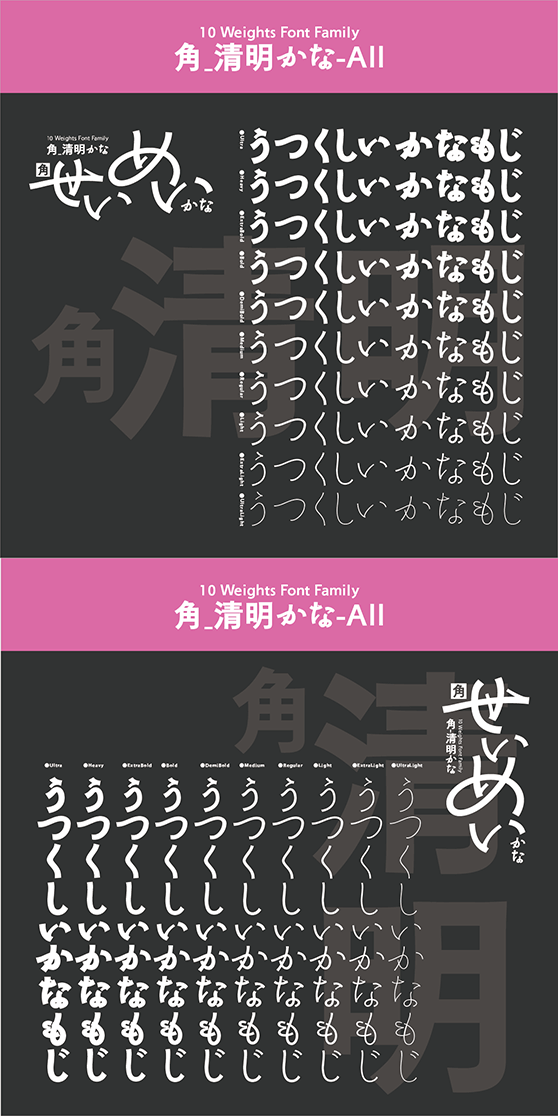
角_清明かな-All (10書体セット)
Kaku_SeimeiKana-UL, Kaku_SeimeiKana-EL, Kaku_SeimeiKana-R, Kaku_SeimeiKana-M, Kaku_SeimeiKana-DB, Kaku_SeimeiKana-EB, Kaku_SeimeiKana-H, Kaku_SeimeiKana-U
優しさと切れ味をあわせ持つかなフォント
この書体は、大好評を得ている「清明かな」のゴシック版として開発されたものです。書体名の「清明(せいめい)」は、季節の指標である「二十四節気」の5番目の節気のこと。春の息吹があふれ「すべてのものが清らかで生き生きしている」という意味です。その名の通り、伸びやかな切れ味の中に優しさ・優美さを包含した不思議な書体です。
タイプデザイナー金井和夫の普段使いの文字をベースとした、明朝・行書・楷書の複雑なフォルムイメージを持っています。また、オールドなイメージを残しつつも、その概念にとらわれず大仮名に設計してあり、近代的な組版にも対応するマルチな性格を備えています。
角_清明かなは、クリエイティブワークに「躍動感と訴求力を表現する」一助にと開発されました。和文フォントは、正方形の中に押し込めることにより、伸びやかさがなくなる傾向があります。この書体は必ずしも正方形にとらわれない自由な発想で作られています。特徴が強く、長文には不向きですが、短い本文組みや、手紙文、ちょっとした見出しに使ってみてください。躍動感に満ちた、訴求力のある紙面になるはずです。縦組み、横組みともプロポーショナル加工を加えました。また、ペアカーニングもほどこしてあります。